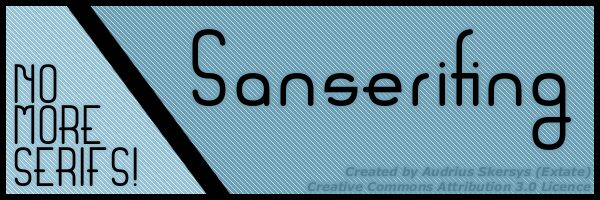
Sanserifing to darmowy, zaokrąglony font typu display o miękkim, geometrycznym charakterze. Jego litery opierają się na gładkich, równych pociągnięciach i szerokich łukach, jednak nietypowe poziome cięcie w literze „e” oraz otwarte kształty sprawiają, że nie wydaje się on zbyt chłodny czy korporacyjny.
Takie połączenie sprawia, że świetnie sprawdza się w ekranach powitalnych aplikacji, nagłówkach plakatów, na opakowaniach, w brandingu skierowanym do dzieci oraz przyjaznej grafice eventowej, gdzie liczy się ciepły przekaz. Jako darmowy font pasuje też do szybkich plansz tytułowych, postów w social mediach i szkiców logo, zwłaszcza gdy szukasz prostych form z jednym lub dwoma zabawnymi detalami, które robią robotę.
Sanserifing
Audrius Skersys (Extate)